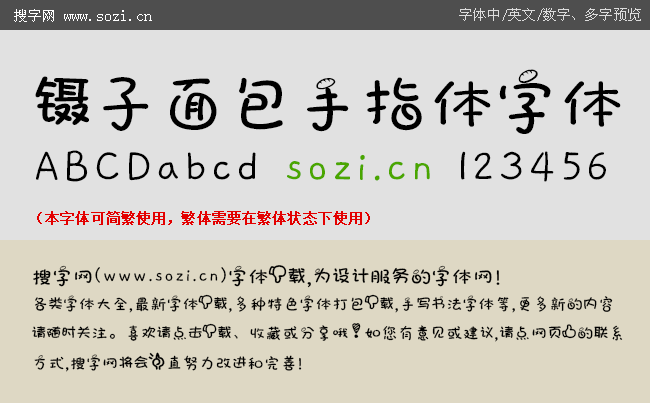
鑷子面包手指體字體
搜字網(wǎng)給大家提供一款很帶有手寫風(fēng)格的卡通手機中文字體下載。修改者將它命名為鑷子面包手指體字體,這款手機字體是在仿照兒童手寫風(fēng)格的卡通手寫字體筆畫間加上卡通圖案。即有卡通字體的趣味性,又有手寫字體的藝術(shù)性,真是童趣十足的一款字體,特別適合喜歡手機字體個性一些的朋友在手機上安裝使用。